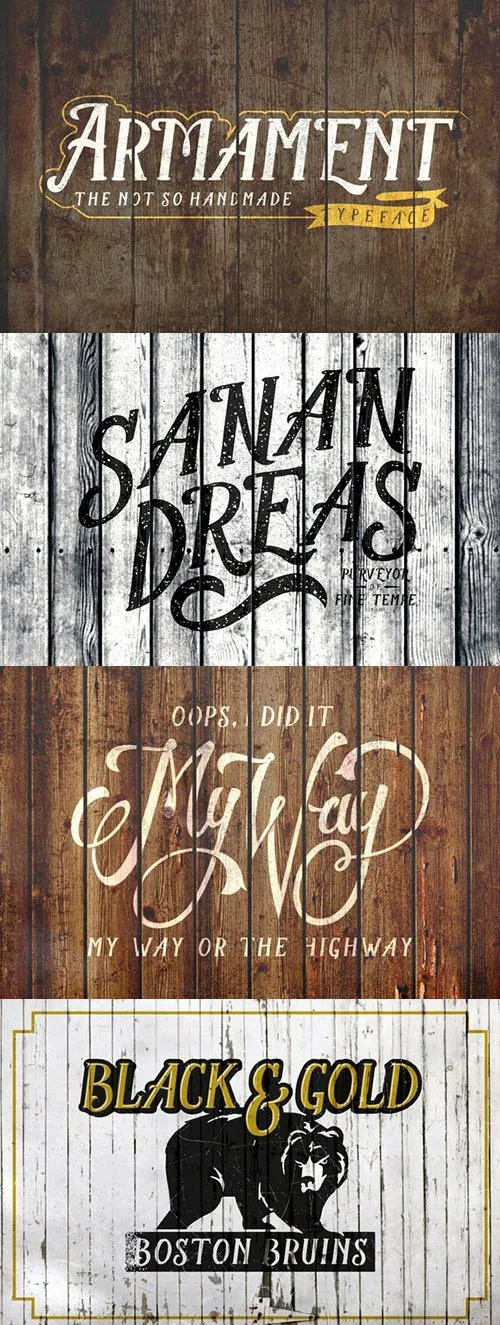
Armament Font – Fonte Grátis
Armament Font
A Armament Font é uma escolha perfeita para designers que procuram adicionar um toque emocionante e inconfundível a seus projetos. Desenvolvida pelo designer Hamilton, essa fonte de display fornece linhas robustas e contrastes intensos que adicionam um impacto visual poderoso ao design gráfico. Com traços finos marcados em sua tipografia, esta font é ideal para criar visuais chamativos que se destacam do resto da página ou layout. Seja você criando uma newsletter de email atraente ou decorando seu site com elementos assertivos e inovadores, a Armament Font é um recurso indispensável na sua biblioteca de fontes. Ela oferece a oportunidade de adicionar elementos que se destacam, capturando a atenção do público e garantindo uma impressão memorável.